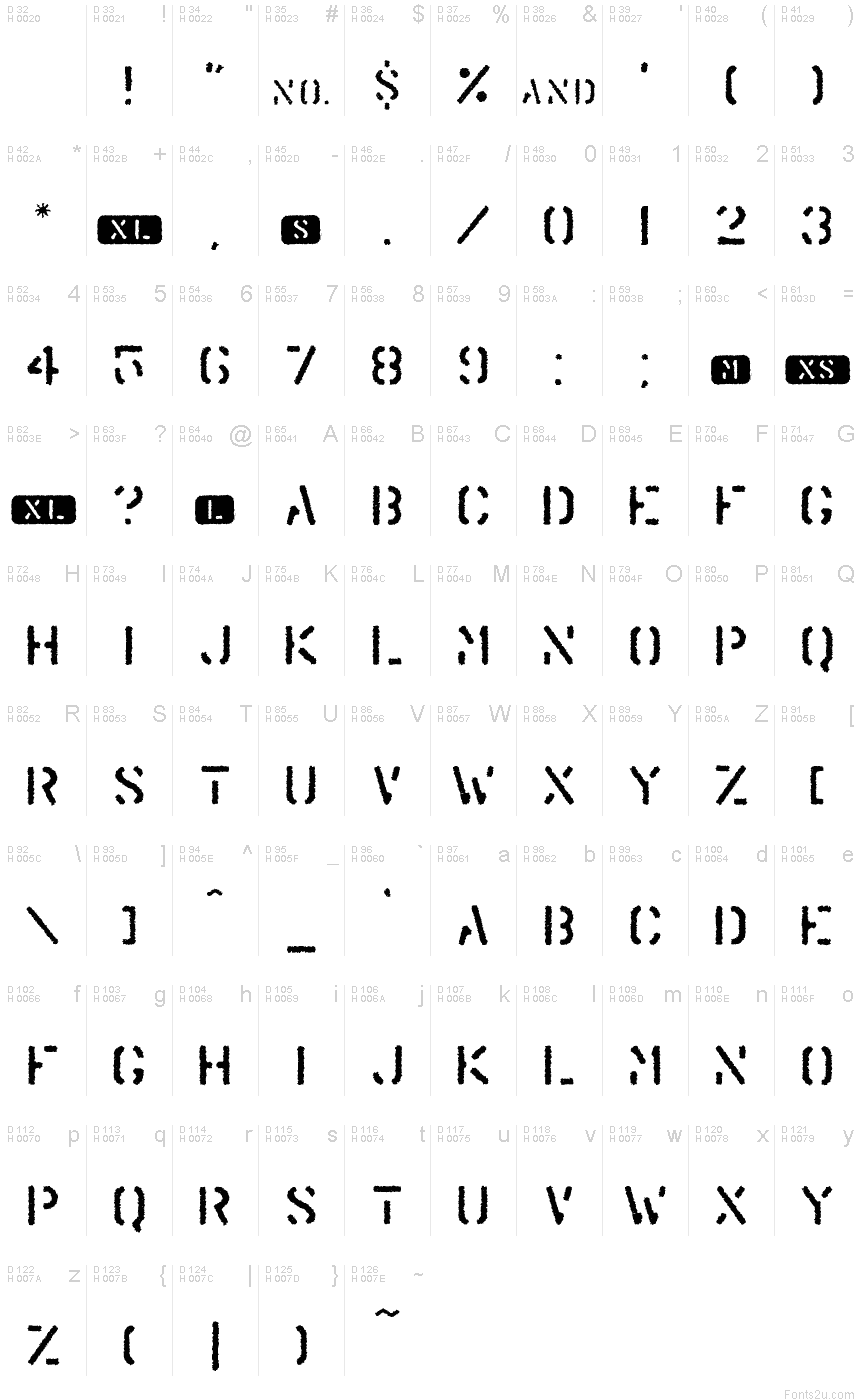
Trendy University من Font"a"licious Fonts هو خط مجاني بتصميم استنسل عسكري متآكل، يتميز بطابع صريح وقاسٍ وكأنه مستوحى مباشرة من اللوحات الإرشادية الصناعية. تبدو الحروف الكبيرة متهالكة ومحببة وغير منتظمة، مع أشكال كتلية سميكة مشطورة بقطع حادة وحواف خشنة، مما يمنح الحروف مظهراً خاماً بعيداً عن التصميم الهندسي المتكلف.
يناسب هذا الخط الملصقات، ومنشورات الفرق الموسيقية، وتصاميم أزياء الشارع، والعناوين، وهوية الألعاب، وعناوين الفعاليات، حيث تكون هناك حاجة لخط مجاني يضفي أجواء عسكرية ميدانية قوية. استخدمه في الأسطر القصيرة، أو الشعارات، أو نصوص الأغلفة عندما تريد أن تبدو الحروف كأنها مختومة، ومخدوشة، وذات لمسة عفوية.